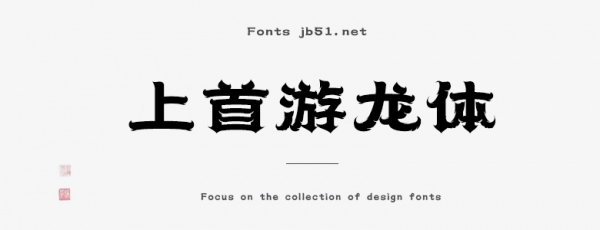
上首游龍體是由上首造字字庫出品的字體,字體字形剛勁有力,棱角分明,適用于搭配標(biāo)志、廣告標(biāo)語、商業(yè)廣告等高端屬性,需要的朋友可以前來本站下載。
上首游龍體,簡體中文約6763字,其字形剛勁有力,棱角分明,如龍得志飛騰于天地,縱橫于四海,其龍角劃破蒼穹,龍須迎風(fēng)浮動,乘風(fēng)而飛,扶搖直上。適用于搭配標(biāo)志、廣告標(biāo)語、商業(yè)廣告等高端屬性。